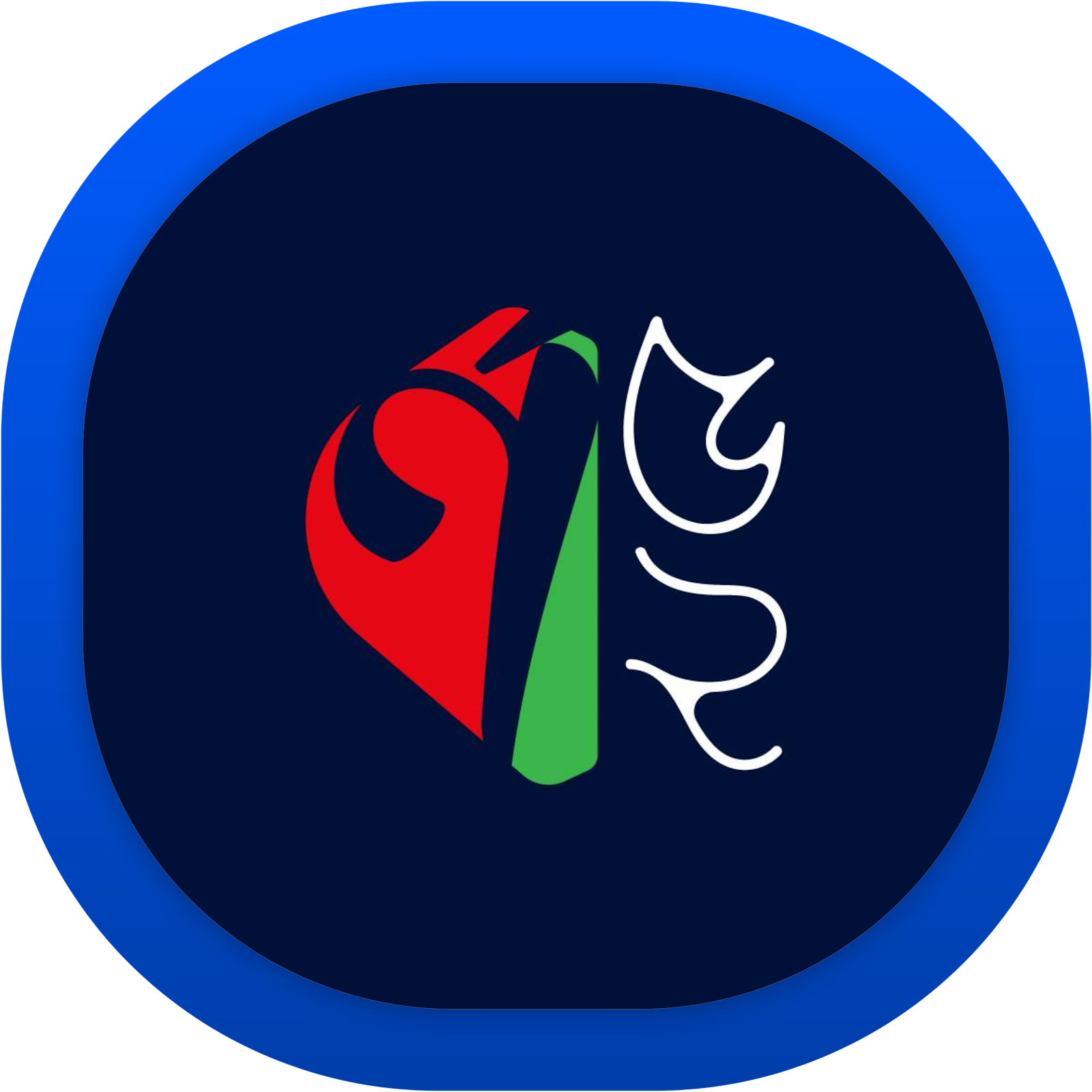
নিগড় একটি ভিন্নধর্মী বাংলা ফন্ট। এটি মূলত একটি প্রিমিয়াম বাংলা ফন্ট। এখানে প্রদত্ত ফন্টটি ফন্টটির একটি ডেমো ভার্সন মাত্র। ফলে ফন্টটিতে কোনো যুক্তবর্ণ নেই। ফন্টটি শুধুমাত্র নামলিপি, ছোট খাটো সাধারণ লাইন ডিজাইনের ক্ষেত্রে ব্যবহারযোগ্য।
নিগড় কালার
- নকশাকার : শাহিদ শরীফ রাসেল
- বিকাশকারী : শাহিদ শরীফ রাসেল এবং মোহাম্মদ আদেল
- ধরণ : ইউনিকোড
- রূপ : ১ টি
- বর্ণের ভাষা : বাংলা